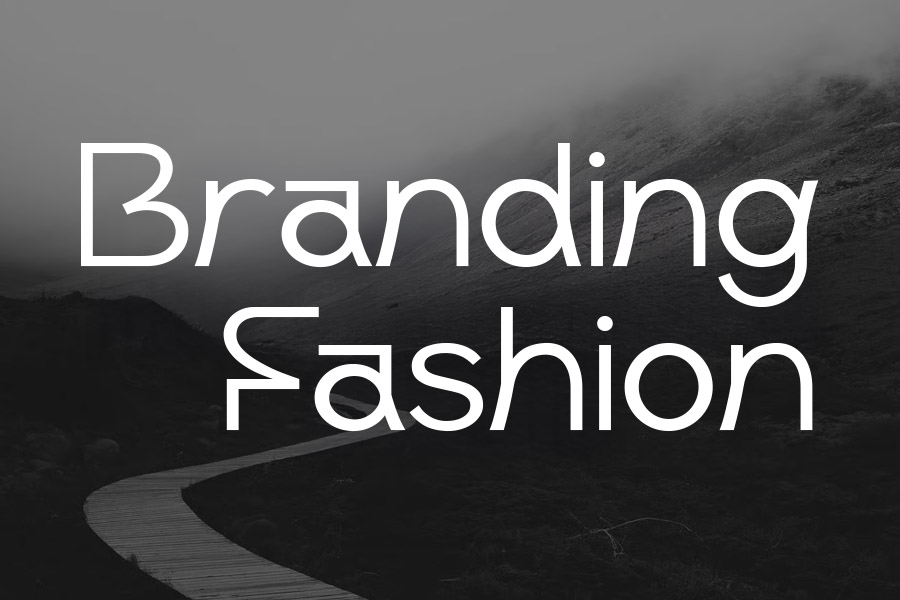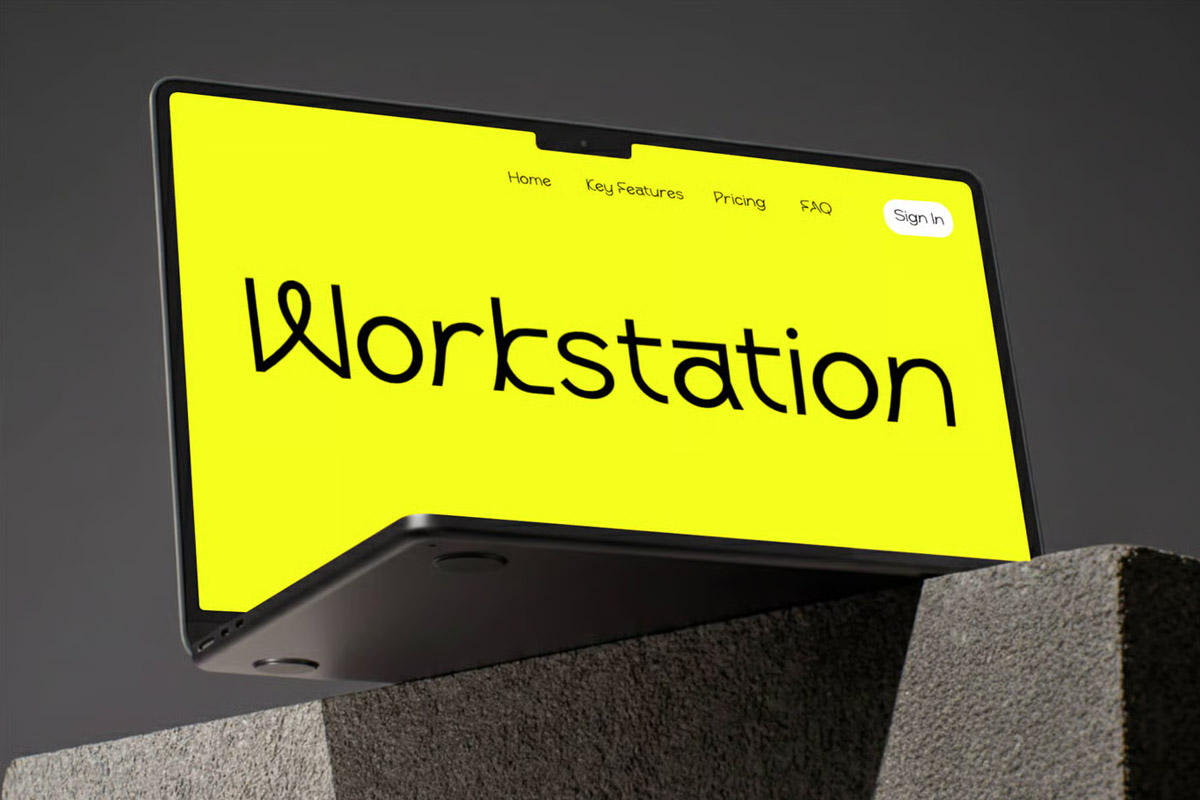
TH Giabe Việt hóa - Phông chữ Sans Serif Display Hiện Đại & Cá Tính Cho Designer
Trong thế giới Typography hiện đại, ranh giới giữa sự tối giản (Minimalism) và tính nghệ thuật (Artistic) thường rất mong manh. TH Giabe chính là cây cầu nối hoàn hảo giữa hai yếu tố đó. Đây là phiên bản Việt hóa hoàn chỉnh từ bộ font gốc Giabe Sans Serif Display đình đám, được Team TH tinh chỉnh kỹ lưỡng để mang lại trải nghiệm gõ tiếng Việt mượt mà nhất cho cộng đồng thiết kế.
Vẻ Đẹp Của Sự Tối Giản Nhưng Không Đơn Điệu
TH Giabe thuộc dòng Sans Serif Display (Chữ không chân dùng cho tiêu đề), mang trong mình hơi thở của thời đại kỹ thuật số 4.0. Khác với những font văn bản thông thường, TH Giabe sở hữu những đường nét gãy gọn, dứt khoát và có độ tương phản độc đáo. Cấu trúc chữ được thiết kế với hình khối vững chãi, tạo cảm giác tin cậy, nhưng vẫn giữ được sự linh hoạt nhờ những đường bo góc tinh tế ở một số ký tự đặc biệt.
Chính sự cân bằng này giúp TH Giabe không bị khô cứng như các font kỹ thuật, mà ngược lại, nó toát lên vẻ "trendy" (thời thượng), rất phù hợp với gu thẩm mỹ của Gen Z và các thương hiệu hướng tới sự đổi mới.
Vũ Khí Bí Mật Cho Branding & Tiêu Đề
Nếu bạn đang tìm kiếm một "giọng nói" to, rõ và đầy sức hút cho thương hiệu, TH Giabe là lựa chọn không thể bỏ qua. Nhờ đặc tính Display, font chữ này phát huy sức mạnh tối đa khi được đặt ở kích thước lớn.
Thiết kế Logo: Tạo nên những logo chữ (Logotype) hiện đại, dễ nhớ và cực kỳ chuyên nghiệp.
Poster & Banner: Giúp các dòng Headline (Tiêu đề) nổi bật ngay lập tức giữa hàng tá thông tin, thu hút ánh nhìn của người xem chỉ trong vài giây đầu tiên.
Bao bì & Tạp chí: Mang lại vẻ ngoài sang trọng, sạch sẽ (Clean look) cho các ấn phẩm thời trang, mỹ phẩm hoặc công nghệ.
Bản Việt Hóa "Có Tâm" Từ Team TH
Giá trị lớn nhất của bộ font này nằm ở hậu tố "TH". Hiểu được nỗi đau của Designer khi tìm được font đẹp nhưng lại lỗi dấu, Team TH đã dành nhiều tâm huyết để Việt hóa TH Giabe.
Dấu câu chuẩn chỉnh: Các ký tự đặc thù như ư, ơ, đ, ê, ô được vẽ lại dấu tỉ mỉ, đảm bảo độ cao và khoảng cách hài hòa với tổng thể con chữ, không bị lệch lạc hay "nhảy dòng" khó chịu.
Kerning tối ưu: Khoảng cách giữa các cặp ký tự tiếng Việt đã được căn chỉnh lại, giúp văn bản hiển thị liền mạch và thẩm mỹ hơn.